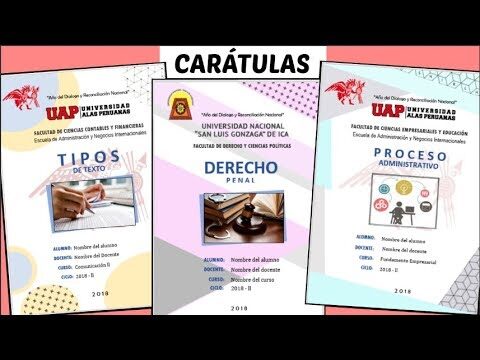
Diseño de portafolios: Tipografía innovadora
En el mundo del diseño, la tipografía juega un papel fundamental en la creación de portafolios impactantes y memorables. Descubre cómo utilizar tipografía innovadora para destacar tu trabajo y cautivar a tus clientes potenciales. Con estos consejos, podrás elevar la presentación de tus proyectos a un nivel superior y dejar una impresión duradera en la industria del diseño. ¡No te pierdas esta oportunidad de destacar con estilo y creatividad!
¿Cuál es el tipo de letra más profesional?
El tamaño más adecuado de letra para un currículum sería aproximadamente de 11 para el contenido (dependiendo de la fuente) y de 14 para los títulos de cada apartado, además de para el nombre y apellidos. Las fuentes más recomendadas para un CV serían Cambria, Garamond, Arial o Georgia. Asegurarse de utilizar un tipo de letra profesional y legible es crucial para transmitir una imagen profesional y organizada a los reclutadores. Por lo tanto, elegir una fuente clara y con buena legibilidad es fundamental para destacar la información de manera efectiva.
¿Cuál tipo de letra es más llamativo?
Las tipografías serif o con serifa son las más clásicas y antiguas, ideales para impresión y publicaciones con mucho texto. Su presencia en libros, periódicos y revistas aporta un toque clásico, serio y tradicional, facilitando la lectura rápida gracias a la serif.
Por otro lado, las tipografías sans-serif son más modernas y limpias, ideales para diseños digitales y pantallas. Su simplicidad y falta de adornos las hacen ideales para transmitir un mensaje claro y directo, atrayendo la atención de manera efectiva en entornos digitales.
¿Cuál es la tipografía moderna?
Las fuentes modernas son conocidas por su elegancia y atrevimiento, con un estilo distintivo que las hace ideales para encabezados y logotipos. A menudo presentan serif, aunque no siempre, y a veces se clasifican como fuentes cursivas. Su diseño afilado y profesional las hace destacar en cualquier contexto.
Estas tipografías destacan por su carácter distintivo y profesional, lo que las convierte en la elección perfecta para proyectos que requieren un toque de elegancia y estilo. Su versatilidad las hace adecuadas para una amplia gama de aplicaciones, desde diseño gráfico hasta publicidad, donde su impacto inmediato las hace sobresalir.
En resumen, las fuentes modernas se caracterizan por su audacia, elegancia y estilo distintivo. Su diseño afilado y profesional, a menudo con serif o cursivas, las hace ideales para encabezados y logotipos, así como para proyectos que buscan destacar con un toque de clase y sofisticación.
Impacta con tu presentación: Diseño de portafolios con tipografía innovadora
En un mundo cada vez más visual y digital, el diseño de portafolios juega un papel fundamental en la presentación de proyectos y habilidades. Utilizar una tipografía innovadora puede marcar la diferencia al captar la atención del espectador y comunicar de manera efectiva el mensaje que se desea transmitir. La combinación de colores, formas y fuentes de letras creativas puede impactar de manera positiva en la percepción de nuestro trabajo, destacando nuestra creatividad y originalidad. ¡No subestimes el poder de una tipografía bien pensada en tu presentación, puede ser la clave para dejar una impresión duradera!
Eleva tu creatividad: Aprende a usar tipografía innovadora en tus portafolios
Descubre cómo dar un toque único a tus diseños aprendiendo a utilizar tipografías innovadoras en tus proyectos creativos. La tipografía es una herramienta poderosa que puede elevar la apariencia visual de tus portafolios y captar la atención de tus espectadores de manera efectiva. Aprende a jugar con diferentes estilos, tamaños y colores de letras para crear composiciones impresionantes y originales.
En lugar de optar por las tipografías tradicionales, atrévete a experimentar con fuentes más arriesgadas y modernas que reflejen tu personalidad y estilo único. La elección de la tipografía adecuada puede transmitir el mensaje correcto y destacar la información clave en tus diseños. Aprende a equilibrar la legibilidad con la creatividad para lograr un impacto visual memorable en tus portafolios.
Aprender a utilizar tipografía innovadora en tus portafolios te permitirá diferenciarte de la competencia y mostrar tu talento de una manera única y distintiva. Dedica tiempo a explorar nuevas fuentes, experimentar con diseños tipográficos y encontrar la combinación perfecta que resalte tus habilidades y proyectos. Eleva tu creatividad y sorprende a tus clientes y seguidores con diseños tipográficos que dejen una impresión duradera.
Diseño de portafolios: Cómo destacar con tipografía creativa
En el mundo del diseño de portafolios, la tipografía creativa puede marcar la diferencia entre destacar o pasar desapercibido. La elección de fuentes únicas y llamativas puede captar la atención del espectador de manera instantánea, transmitiendo personalidad y originalidad a cada proyecto presentado. Al combinar tipografías en diferentes tamaños, pesos y estilos, se puede crear un diseño visualmente atractivo y memorable que refleje la creatividad y profesionalismo del diseñador. La tipografía no solo cumple una función estética, sino que también comunica el mensaje de manera efectiva, guiando al espectador a través del contenido de forma clara y coherente. En definitiva, el uso de tipografía creativa en el diseño de portafolios es una poderosa herramienta para destacar y dejar una impresión duradera en quienes lo observan.